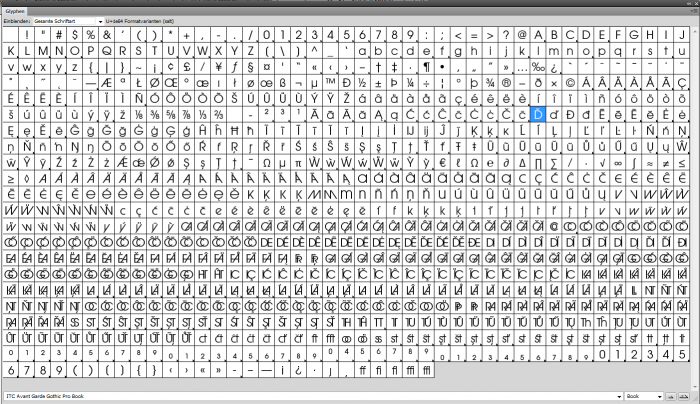
Alternative zu Arrière-garde?
ich suche eine ähnliche bis gleiche Schriftart wie die Arrière-garde. Die Schriftart an sich wäre perfekt aber leider finde ich keinen Hinweis auf die Urheberrechte oder wo ich die Schriftart kaufen kann. Eine lizenzierte Schrift in der Form wäre mir lieber.
Hallo, es geht mir nicht um die reine Schriftart von der Art der Buchstaben, sondern in der Kombination, dass einige Buchstaben in gross und andere in klein sind. Bei der Arriere sind auch einige Buchstaben in gross wie z. B. R oder P und andere in klein wie a, e... Es geht um den Stil der Schrift.
kannst Du mal ein Beispiel der Schrift einstellen? Ist das eine unikamerale Schrift?
edit: Ah, R::bert hat das Rätsel schon gelöst. Habt Ihr dennoch mal ein Beispiel? Disturbance, Bodoni 26, Parity und Grote sind ja auch Unicase-Schriften, aber total unterschiedliche. Da wäre hilfreich zu wissen, was für eine Formensprache die Ausgangsschrift hat.
Ja, das wollte ich eben auch noch ergänzen. Die Avant Garde Pro ist das Original und enthält alle Zeichen, die Du suchst. Du musst Dir nur mal die Glyphenansicht ansehen.
Hallo, danke schon mal für die Tipps. Es soll so eine Schrift sein, wie im Beispiel mit der Arriere Garde . Diese soll professionell eingesetzt werden, deswegen am liebsten auf Lizenzbasis damit es keine rechtlichen Schwierigkeiten gibt.
Genau das lässt sich mit der hier genannten Avant Garde Pro und einem opentype-fähigen Satzprogramm (z.B. Adobe InDesign) professionell bewerkstelligen. Du müsstest den Font nur noch kaufen/lizensieren.
darf ich fragen: wie gut kennst Du Dich mit Schrift und Typografie aus? Sagt Dir der Begriff »unikameral« beziehungsweise »unicase« etwas? Arbeitest Du mit Programmen, die mit Open-Type-Funktionen umgehen können? Die von den Kollegen genannte Schrift Avant Garde Pro sieht vom Charakter so aus wie die von Dir genannte Schrift. Und in ihrem erweiterten zeichensatz hat sie die von Dir gewünschten Alternativbuchstaben. Die Avant Garde Pro kannst Du ganz problemlos kommerziell lizenzieren und dann nutzen, sofern Deine Software mit den Features der Schrift zurechtkommt.
Unter dem oben in Ralfs Beitrag eingebetteten Link kannst Du Dir die Schrift bei MyFonts anschauen. Und wenn Du Dir die Glyphentabelle ansiehst, dann findest Du die gewünschten Alternativbuchstaben. In InDesign zum Beispiel lassen sich diese Buchstaben statt der »regulären« Zeichen auswählen, auch automatisch. Das heißt, Du musst natürlich nicht jeden einzelnen Buchstaben separat ersetzen.
eine kurze Frage noch zur Schriftart Avant Garde. Bei myfonts gibt es diese Schrift https://www.myfonts.com/fonts/itc/avant-garde-gothic/pro-book/specs.html. Ist das die Schrift mit den ich den obigen Schriftzug genau so in der Art gestalten kann? Also die Buchstaben müssen genau so in klein und groß sein.
Das Programm dazu habe ich, Illustrator und Indesign. Wie wähle ich dann die Glypen aus? Sind die im normalen Schriftsatz enthalten oder über einen Menüpunkt?
Normalerweise gehst Du in Indesign über die Option Open Type und dort hast Du dann diverse Optionen zur Auswahl - je nachdem, was die Schrift so mitbringt an Zeichen und Alternativen.
Hallo, ich muss das Thema nochmals aufgreifen. Die Schriftart Avant Garde Gothic Pro hab ich gekauft. Aber leider finde ich die Kombination der Buchstaben nicht wie in meinem Beispiel von oben. Entweder sind die Buchstaben klein oder groß, aber von der Höhe her dann unterschiedlich.
Ich hab mal die Glyphen beigefügt. Wie kriege ich jetzt hin, dass die Anfangsbuchstaben wun... und dann osan in klein sind und der Rest in Großbuchstaben, aber in einer Höhe?
ich verstehe es nicht, wenn ich die Buchstaben aus den Glyphen zusammenstelle, kriege ich das Ergebnis was aber nicht das ist was ich oben als Beispiel eingestellt hatte. Wie schaffe ich es, dass alle Buchstaben die gleiche Höhe bekommen?
du gibst – in großbuchstaben – ›WUNDPROSAN‹ in indesign ein und markierst den text. dann klickst du im zeichenbedienfeld (aktivieren mit strg/befehl + t) ganz oben rechts auf das menüsymbol (ein kleiner pfeil und vier striche), wählst im sich öffnenden menü ›opentype‹ aus und weiter ›formatsätze‹. in diesem menü wählst du (bei nach wie vor markiertem text) ›satz 5‹ aus. dann müsstest du die darstellung haben, die du gezeigt hast. wenn’s nicht klappt, dann schreib noch mal, an welchem schritt du nicht mehr weiterkommst.